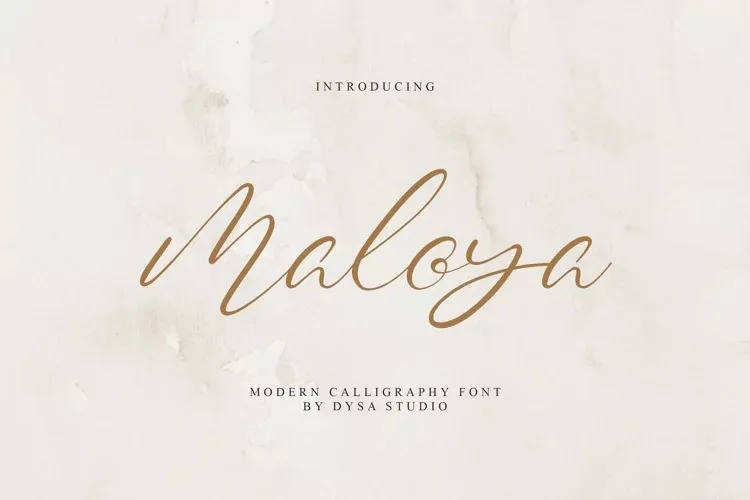
A Maloya é uma elegante fonte tipográfica script criada pela DYSA Studio. Com seu aspecto limpo, fino e macio, esta fonte é perfeita para adicionar um toque sofisticado a qualquer projeto de design. Ideal tanto para novos projetos de marca quanto para as necessidades diárias da sua empresa, ela transmite uma sensação autêntica de arte manual, graças aos seus contornos naturais e ao seu estilo de escrita artesanal. Seja em um cartão de visita, uma camiseta ou até mesmo no interior de um livro, a Maloya traz uma qualidade única que não pode ser desconsiderada. Combinando elegância com versatilidade, esta fonte é certamente uma escolha inteligente para qualquer designer gráfico que busca criar designs autênticos e sofisticados.